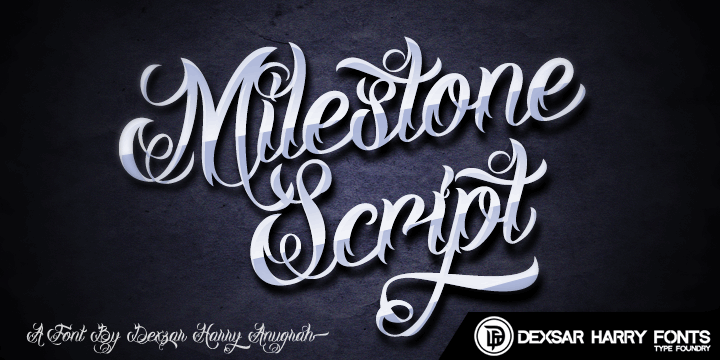
DHF Milestone Script font – Download Grátis
A fonte ‘DHF Milestone Script’ oferece um design elegante e fluido que será perfeito para qualquer projeto de texto elaborado. Conhecida por sua consistência única, a fonte combina elementos modernos com uma personalidade mais sofisticada, fazendo-a ideal tanto para gráficos profissionais quanto para designs de marca. Idealmente projetada pela Mansgreback Hamilton em 2014, esta fonte é perfeita para aqueles que buscam um elemento distintivo para seus trabalhos. Ela tem uma aparência minimalista sem perder o brilho e a personalidade necessários para transmitir sua mensagem de forma convincente. A versão ‘DHF Milestone Script’ da Mansgreback Hamilton oferece recursos que vão além do básico, proporcionando uma paleta variada de opções de tamanho e estilo. É perfeita para criar um texto chamativo ou elegante, dependendo da necessidade específica do seu projeto. Compre a fonte e revigore sua próxima composição, transformando-a em algo único e impecavelmente detalhado. A fonte é uma escolha certa para quem busca transmitir confiança, competência e modernidade, de maneira que ela se destaque claramente. Seja em banners, logotipos ou design web, a fonte ‘DHF Milestone Script’ de Hamilton não apenas adicionará um tom de profissionalismo à sua obra, mas também garantirá que seu trabalho seja lembrado e respeitado como o melhor possível.